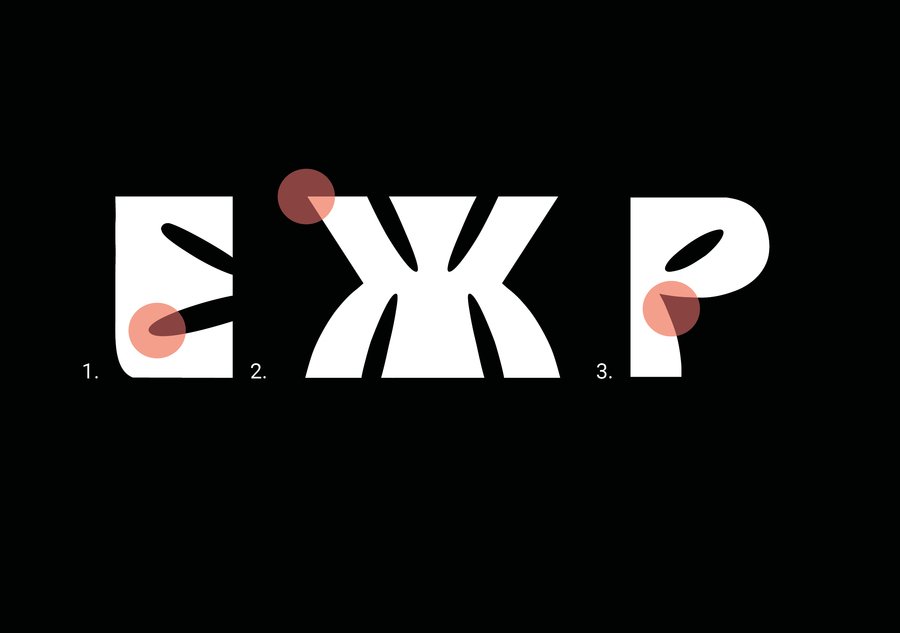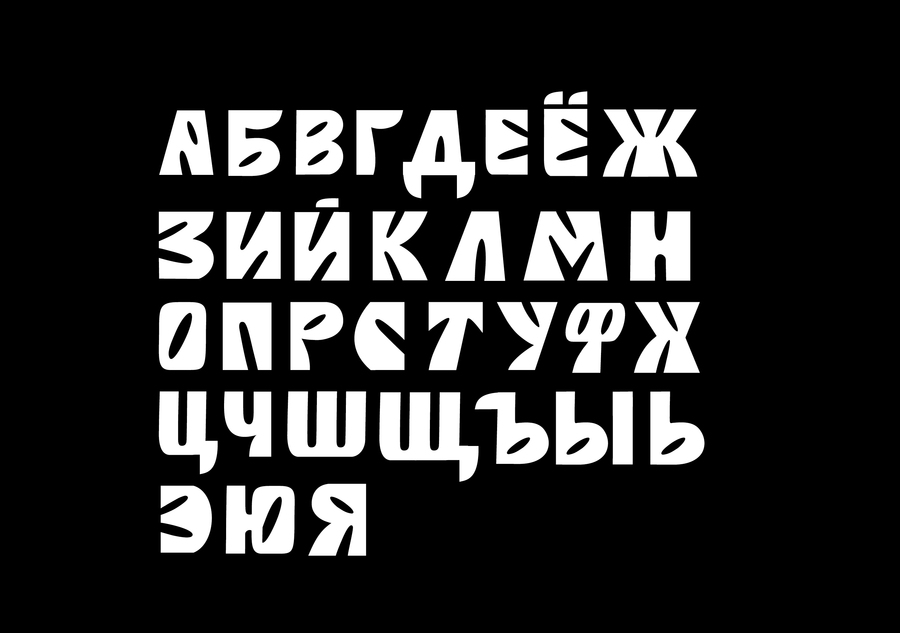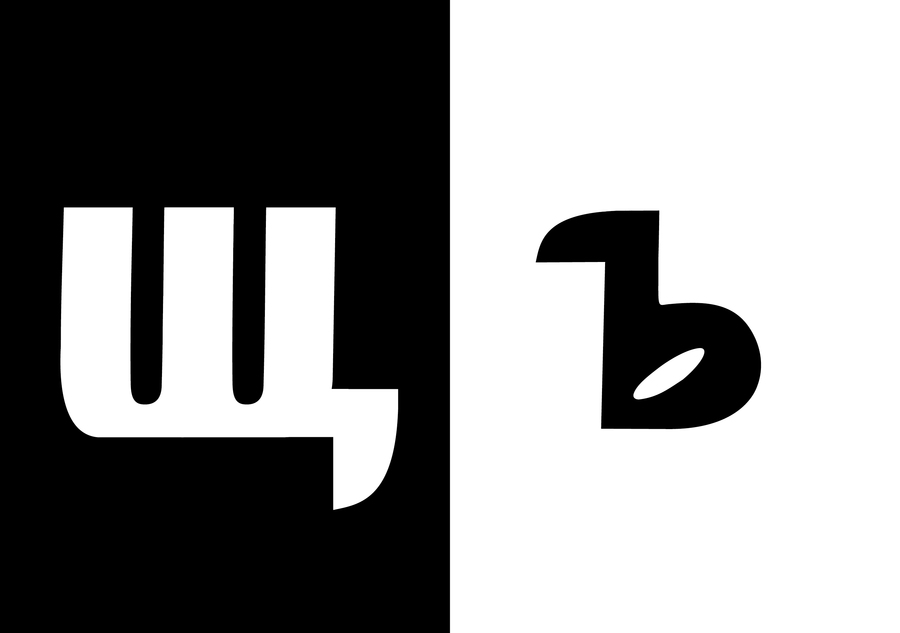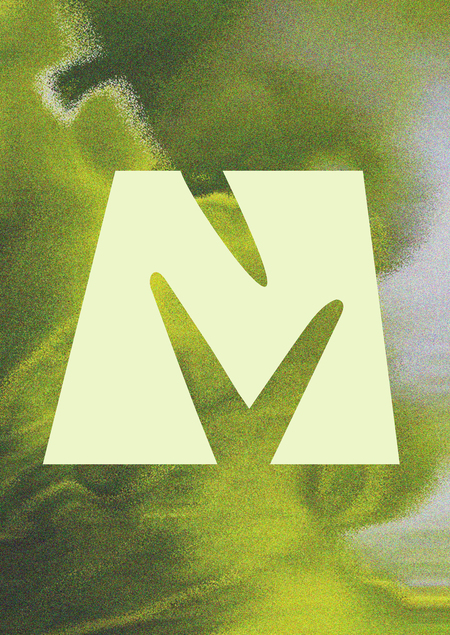
Акцидентный шрифт, который вдохновлён джунглями. Он сочетает дикие формы с силуэтами тропических листьев. Широкие, уверенные буквы, как стволы древних деревьев. Общая форма сохраняет энергию дикой природы, но выглядит более пластичной и естественной.
1 — скругленные вырезы внутри 2 — прямые углы 3 — скругленная «ножка»
кириллица
латиница
цифры и символы